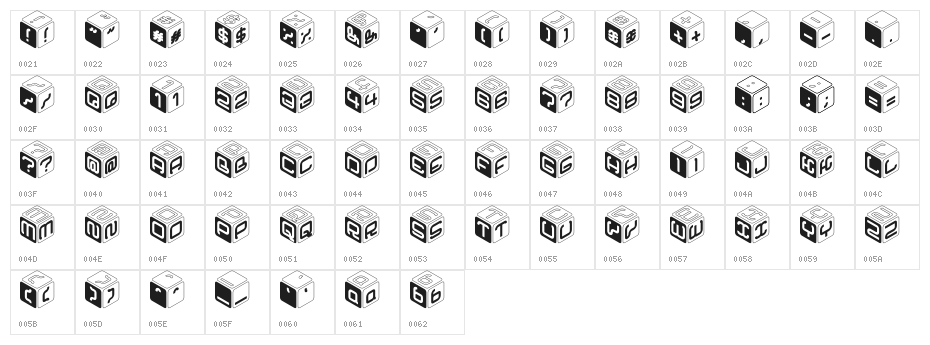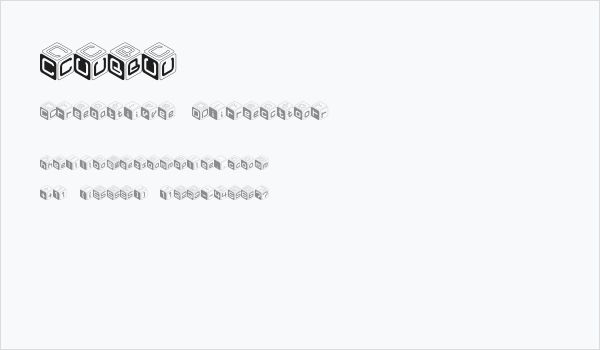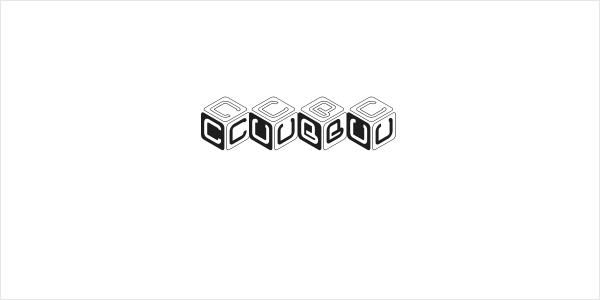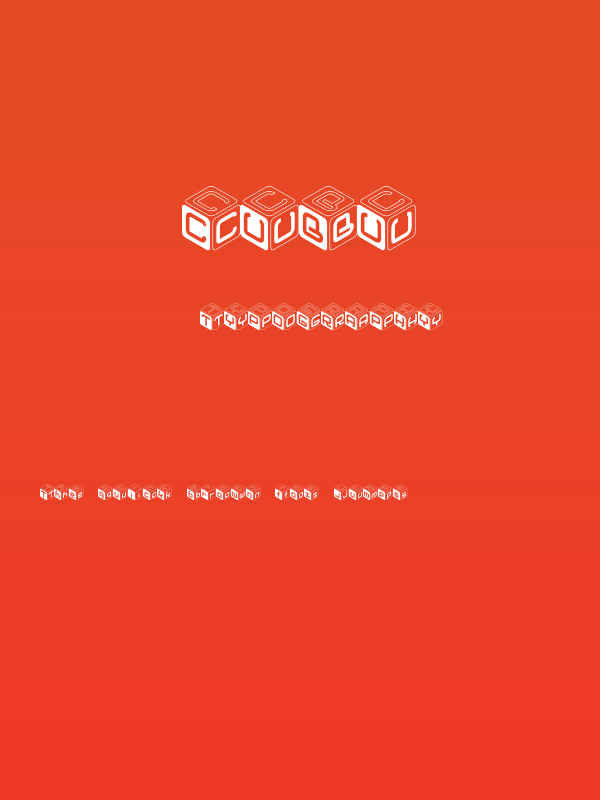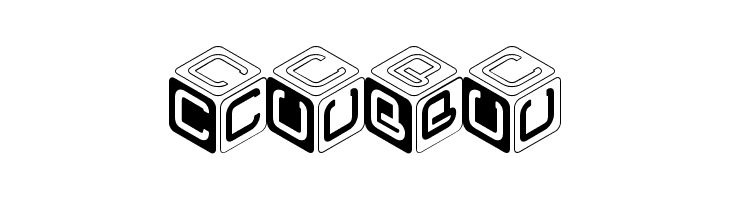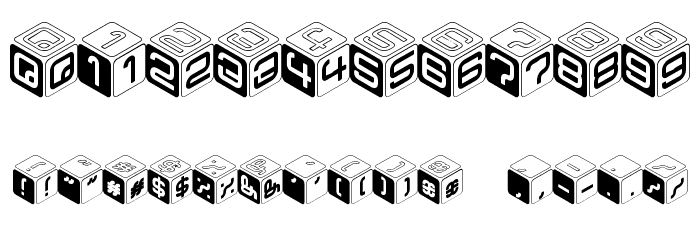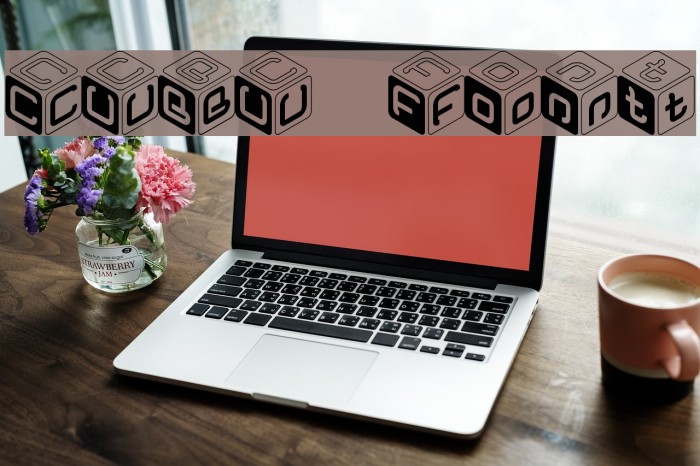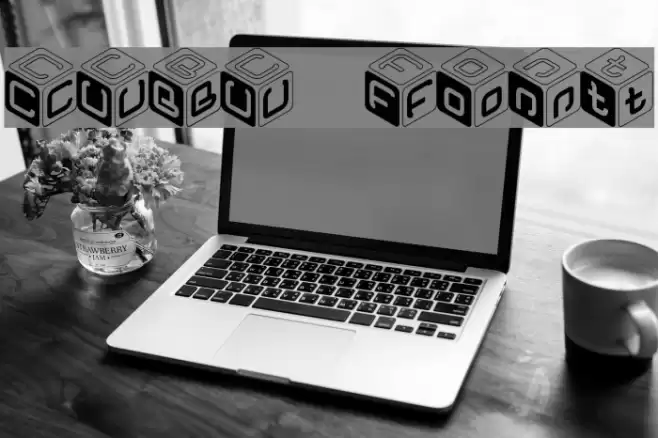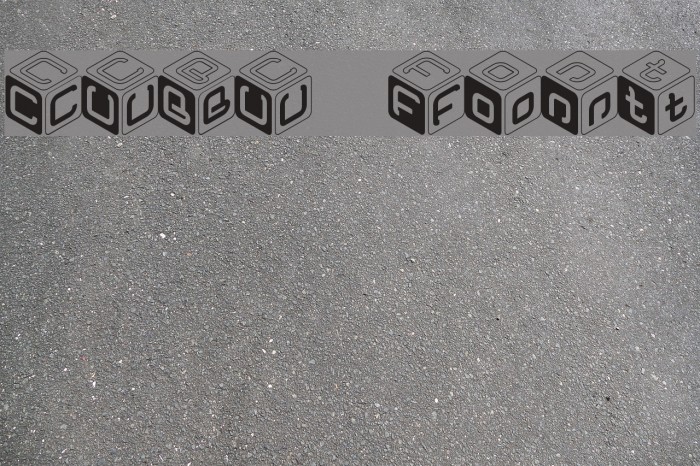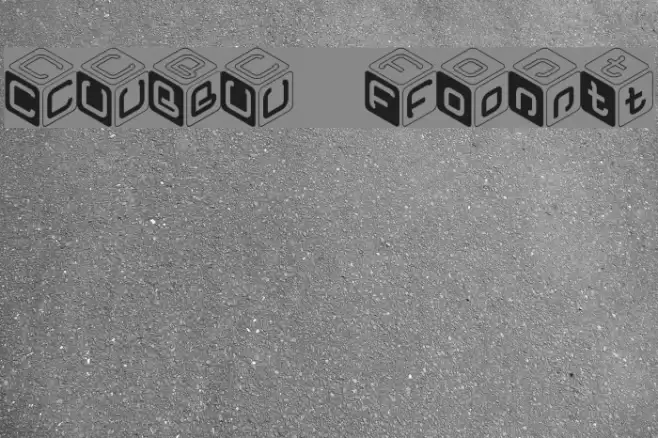
CUBU Font
| Projetos propostos | Ideal for creative projects such as children's book covers, playful branding, video game graphics, or any design requiring a fun and eye-catching typeface. |